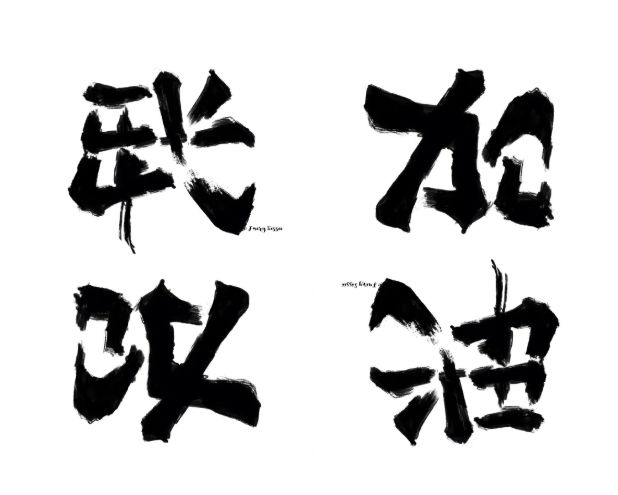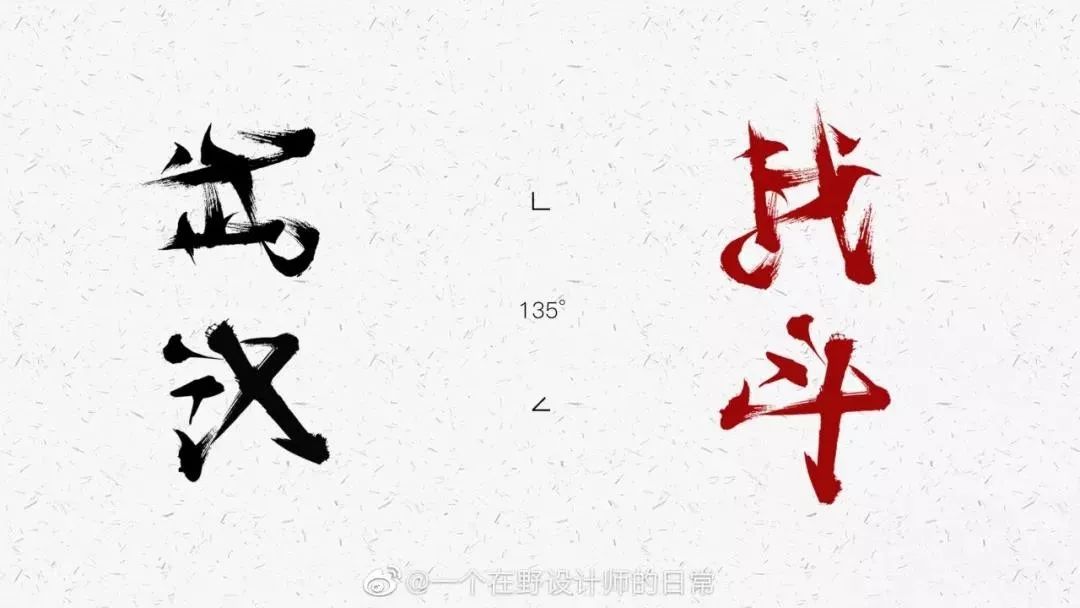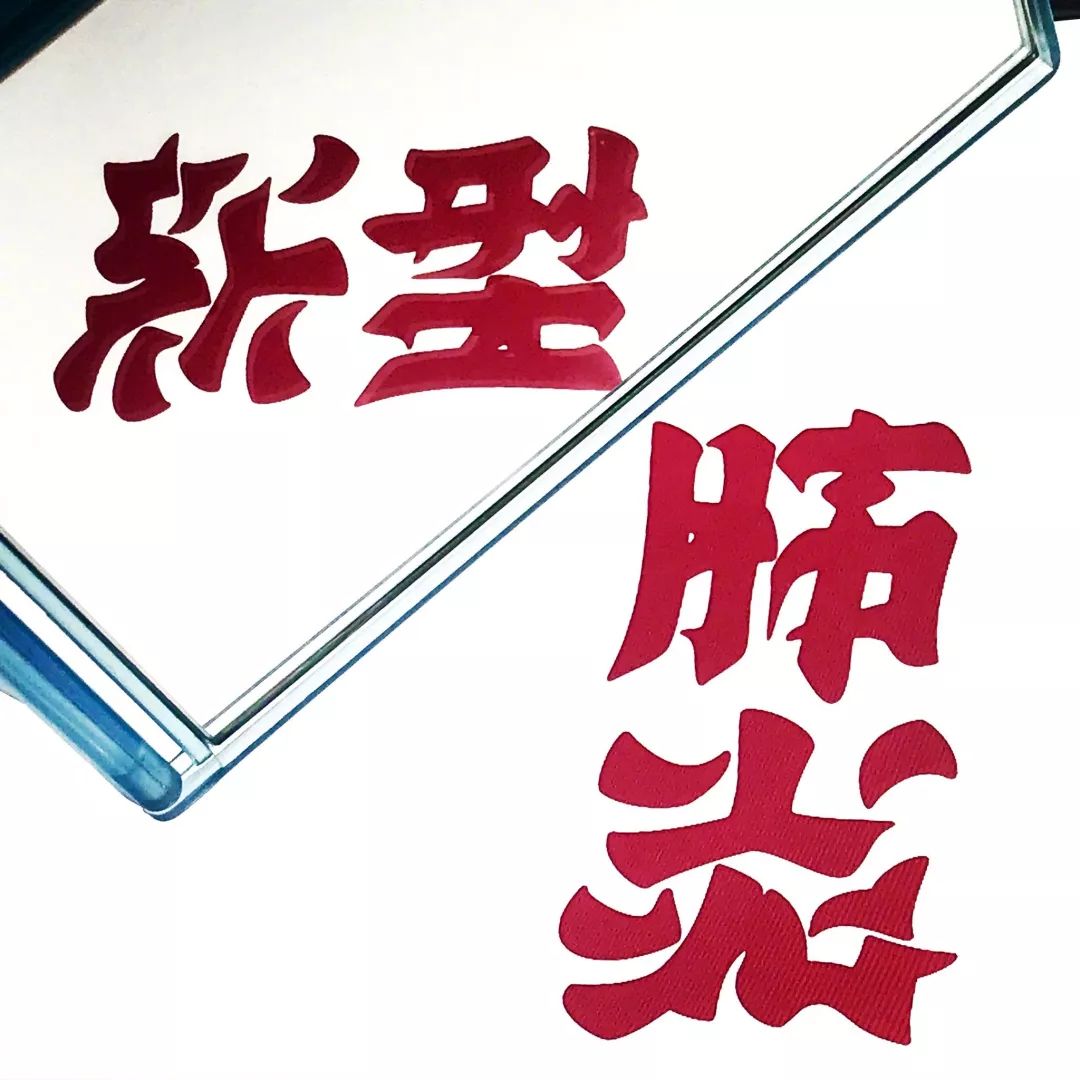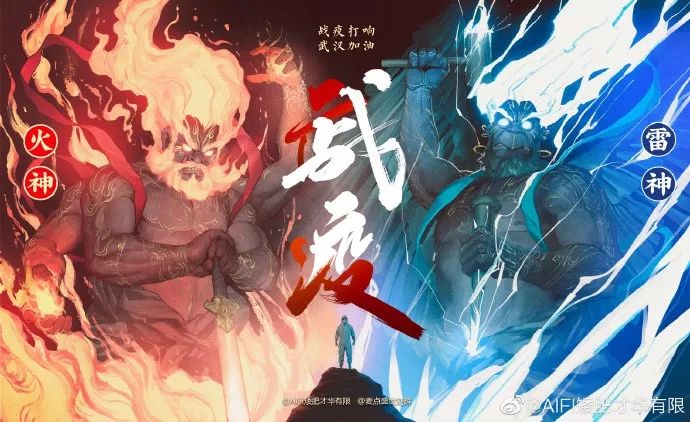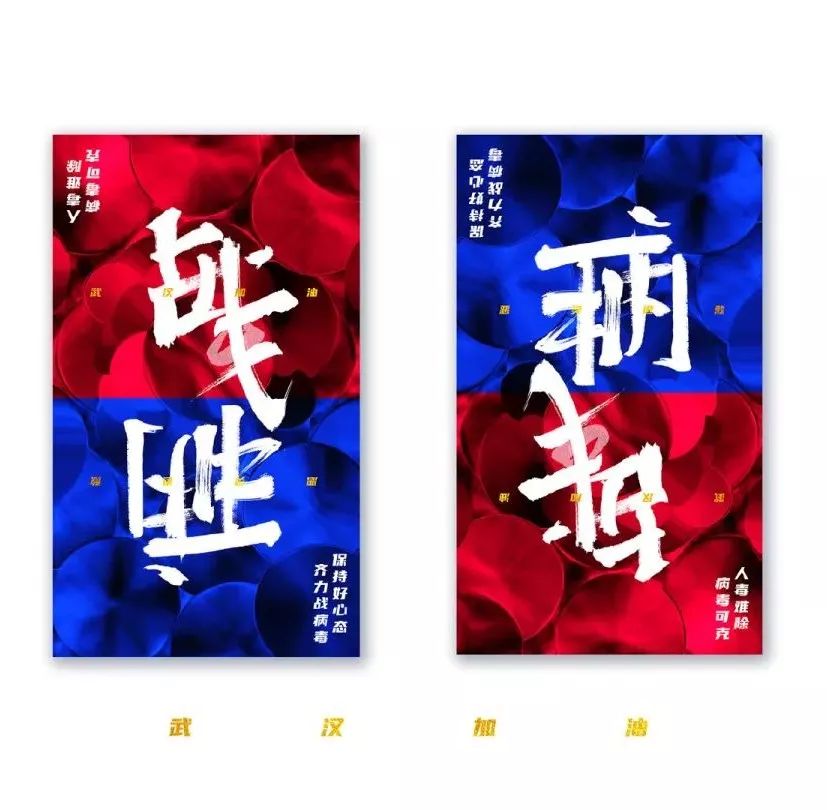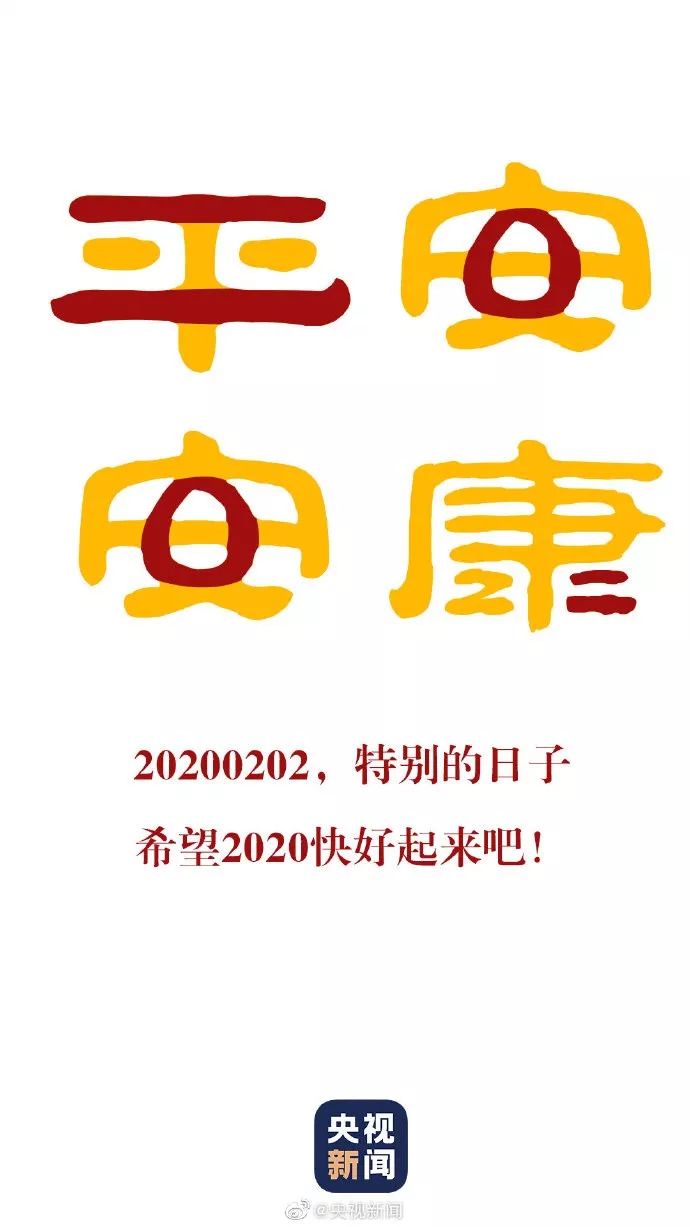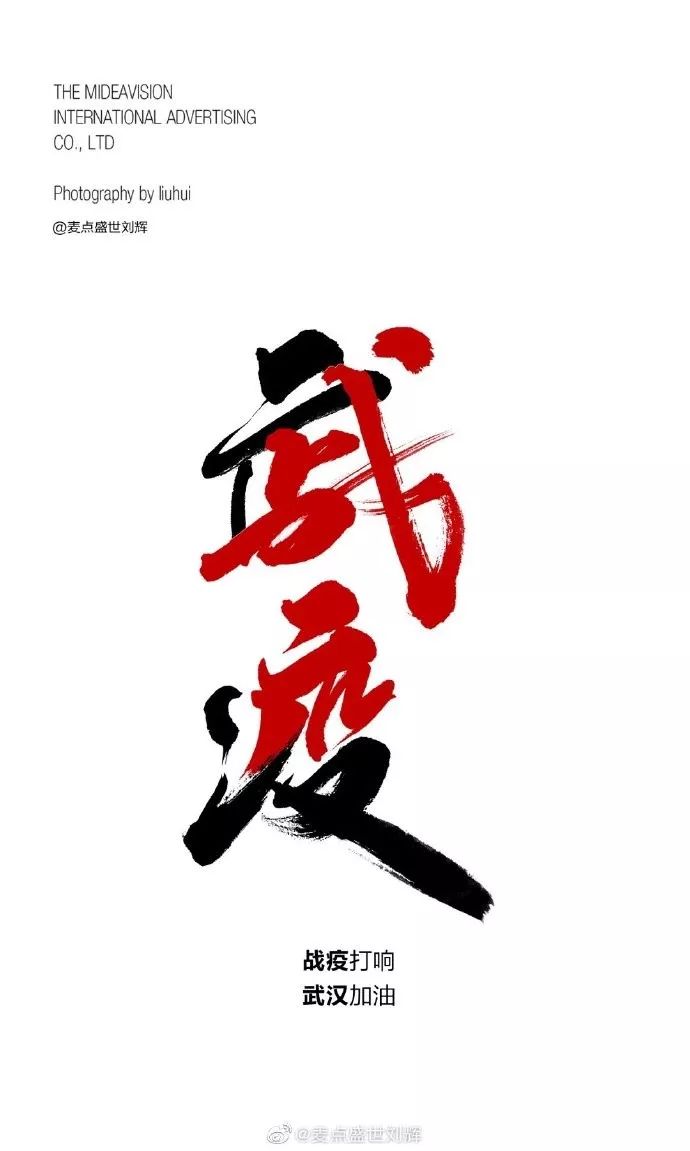
设计师在字里行间,为武汉加油!
毕竟设计师这个职业,只要有电脑和画笔,就可以创造出无限的能量。
双向字
还记得那个很厉害的翻转文字大师,野村一晟吗?这次他也针对疫情创造了新作品——新型⇆肺炎,镜像翻转45度试试~
@王左中右的的创意字,当然也必不可少。
还有其它设计师上下颠倒、左右旋转的双向字。
多意字
除了双向字,还有一种是通过笔画增减,达到一语双关的效果。
宋慧乔刘亚仁ins的应援,wuhan=human
免费字
如果说前面两种,需要高手才能搞定,那其他设计师怎么表达爱?当然是优设和字由联合推出的优设标题黑,一个字就是好,两个字就是好用。
有这么多设计师一条心,相信疫情会早一点结束~